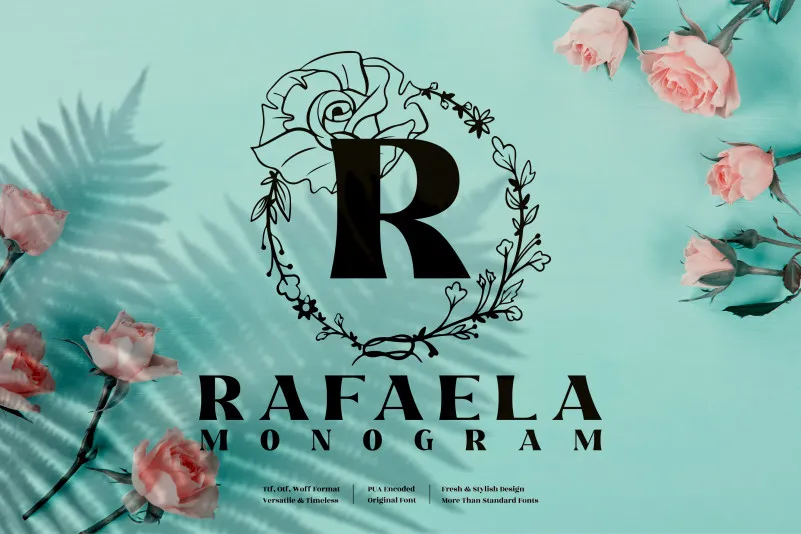
Rafaela Monogram Font – Fonte Grátis
Rafaela Monogram Font
A ‘Rafaela Monogram Font’ é uma elegante tipografia decorativa criada pelo designer perspectype que se destaca por suas ornamentações foliares luxuosas e sofisticadas. Perfeita para quem busca um toque de requinte em seus projetos gráficos, esta fonte combina elegância com personalidade, tornando-a uma escolha inteligente para a criação de cartões de aniversário animados e postagens de mídia social impactantes. Além disso, é perfeita para design de logotipos, envelopes decorativos e até mesmo como fontes para invitations nupciais, trazendo um toque único e sofisticado a cada projeto. Sua versatilidade faz dela uma opção ideal tanto para iniciantes quanto para profissionais.